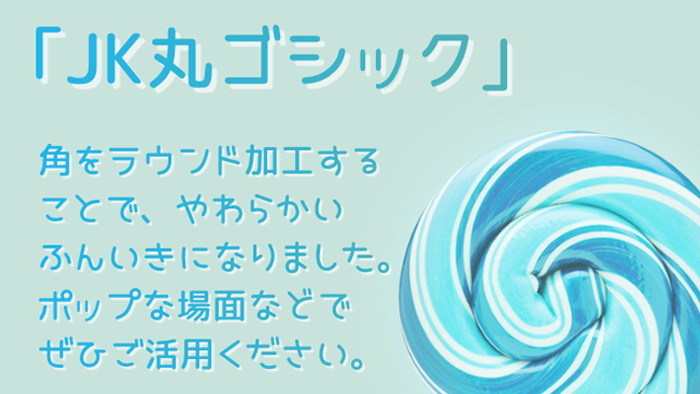
JK丸ゴシックとは、「JKゴシック」に少し加工を加え、女子高生風を意識した可愛らしい全体的に丸っこく、懐は大きめだけど、こじんまりとした文字にラウンド処理を加えた丸ゴシックフォントになっています。
通常のゴシック体より、全体的に丸みがあるので可愛らしい印象があります。子供向けデザインなどのポップなデザインとの相性はとても良さそうです◎
収録文字:仮名文字以外は、オープンソースの「M+ FONTS」で補完させているので、一通りの文字には対応しているようです。